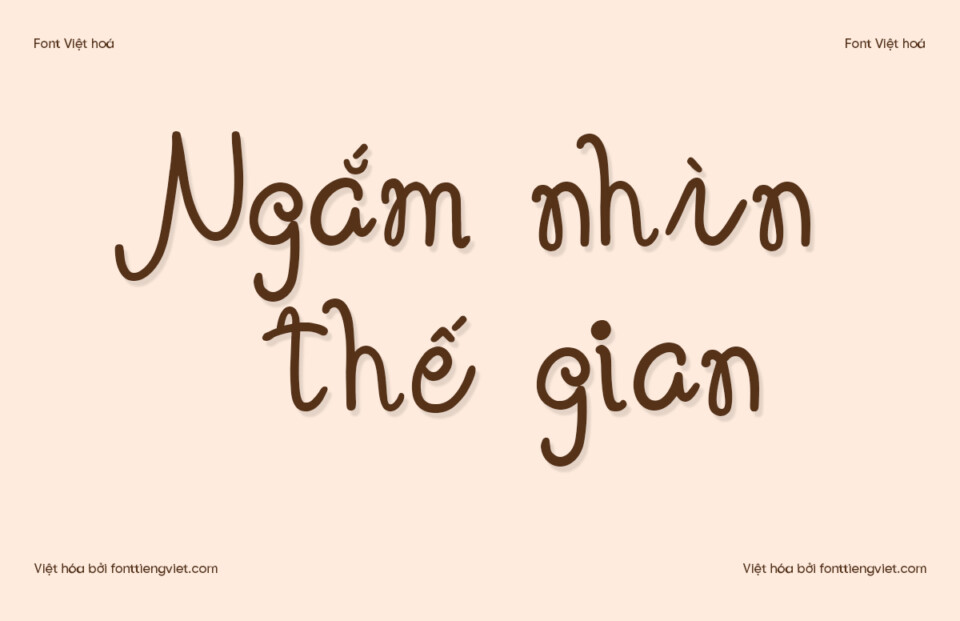
Font Việt hóa 1FTV VIP Marige
Font Việt hóa 1FTV VIP Marige – Font chữ cưới sang trọng, mềm mại
Nếu bạn đang tìm một kiểu chữ mang cảm giác lãng mạn – tinh tế – cao cấp cho các dự án cưới hỏi, thì Font Việt hóa 1FTV VIP Marige là lựa chọn rất đáng thử. Với đường nét uốn lượn mềm mại, các nét nối tự nhiên và tổng thể thanh lịch, font phù hợp để thiết kế thiệp cưới, thiệp mời, hashtag cưới, bảng welcome, menu tiệc, monogram cô dâu – chú rể và cả các ấn phẩm truyền thông trên mạng xã hội.
Điểm nổi bật của Font Việt hóa 1FTV VIP Marige
• Hỗ trợ tiếng Việt đầy đủ: Bộ font đã được Việt hóa chuẩn, hiển thị dấu mượt, hạn chế lỗi ký tự khi gõ.
• Phong cách sang trọng: Nét chữ mềm, bay bổng, hợp chủ đề cưới, thời trang, beauty, branding cao cấp.
• Dễ phối với font khác: Có thể kết hợp cùng font sans/serif tối giản để tạo tương phản đẹp trong layout.
Ứng dụng thực tế: dùng 1FTV VIP Marige cho dự án nào?
Với đặc trưng “script” thanh lịch, 1FTV VIP Marige đặc biệt phù hợp cho các thiết kế cần điểm nhấn cảm xúc:
• Thiệp cưới, thiệp mời, thiệp báo hỷ, sổ ký tên
• Logo studio áo cưới, thương hiệu trang sức, mỹ phẩm
• Cover Facebook/Instagram, banner sự kiện, poster quote
• In ấn bảng welcome, bảng timeline, menu tiệc
Mẹo nhỏ: hãy dùng Marige cho phần tiêu đề/điểm nhấn, còn phần nội dung dài nên phối cùng một font dễ đọc (sans/serif) để bố cục sạch và chuyên nghiệp.